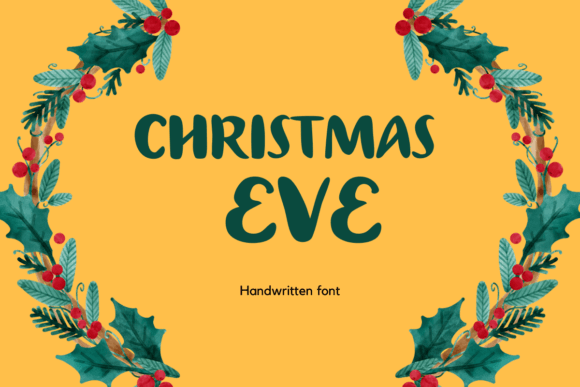
Christmas Eve
適切なデザイン要素を見つけるのは難しい場合がありますが、Christmas Eveは作品を即座に引き立てる優れたコレクションを提供します。
POD(オンデマンド印刷)製品、結婚式の招待状、またはソーシャルメディアのグラフィックを作成している場合でも、Christmas Eveは理想的です。